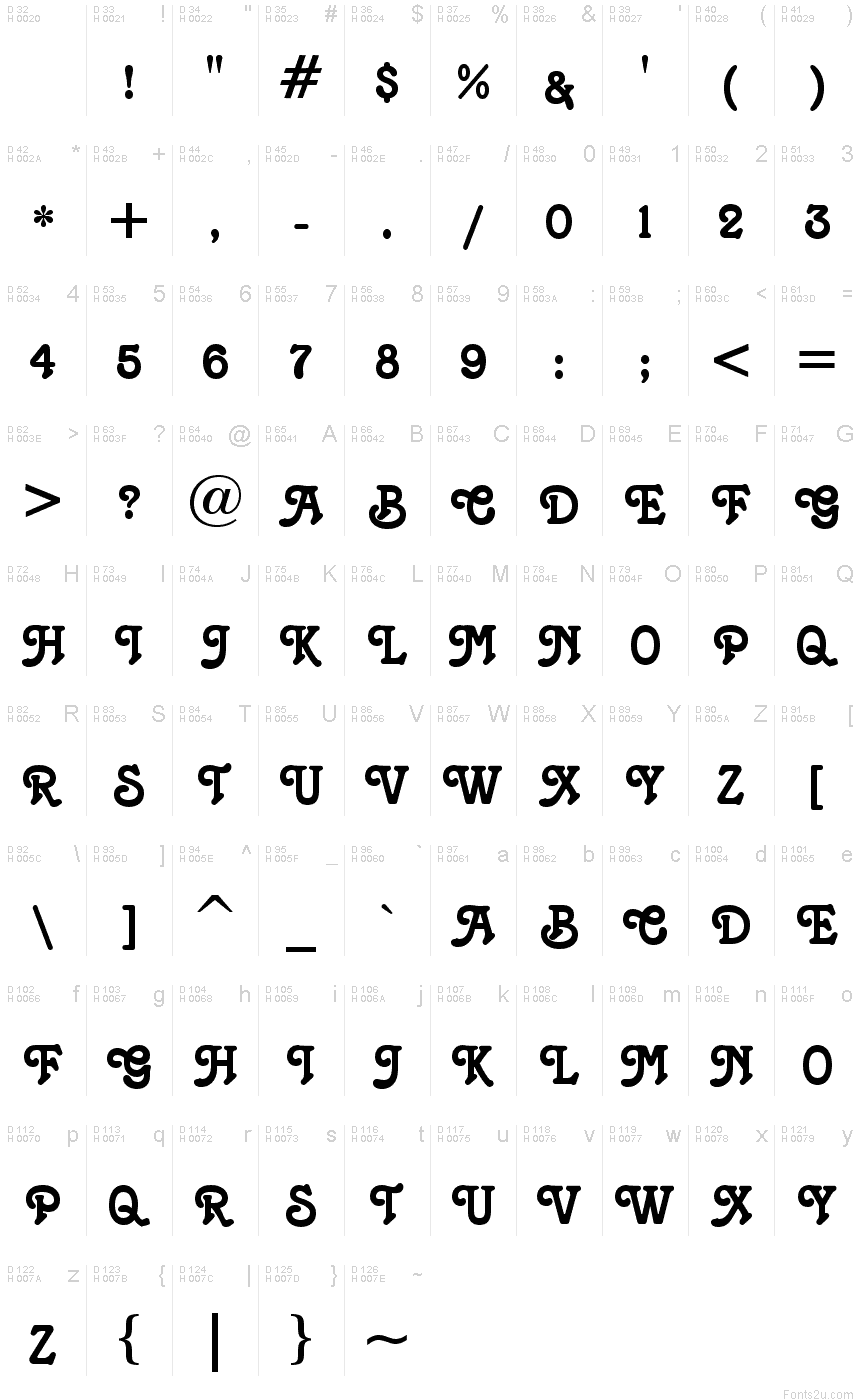
VPS Ba Ria Hoa von VPS Font ist eine kostenlose vietnamesische Zierschrift mit Serifen, die auf großen, geschwungenen Versalien und einem festlichen Old-Style-Rhythmus basiert. Die Buchstaben wirken breit und ausdrucksstark, mit weichen, abgerundeten Verbindungen und kräftigen, ausgestellten Endungen, die der Schrift eher das Flair eines handgemalten Ladenschildes verleihen als den Charakter einer strengen klassischen Serifenschrift.
Sie eignet sich ideal für Restaurant-Branding, Street-Food-Verpackungen, Event-Plakate, Reise-Grafiken und Überschriften, bei denen eine lokale, feierliche Note gefragt ist. Als kostenlose Schrift funktioniert sie auch hervorragend für kurze Titel, Monogramme und Initialen, da die geschwungenen Versalien genug Dynamik mitbringen, um selbst mit wenigen Buchstaben zu wirken.